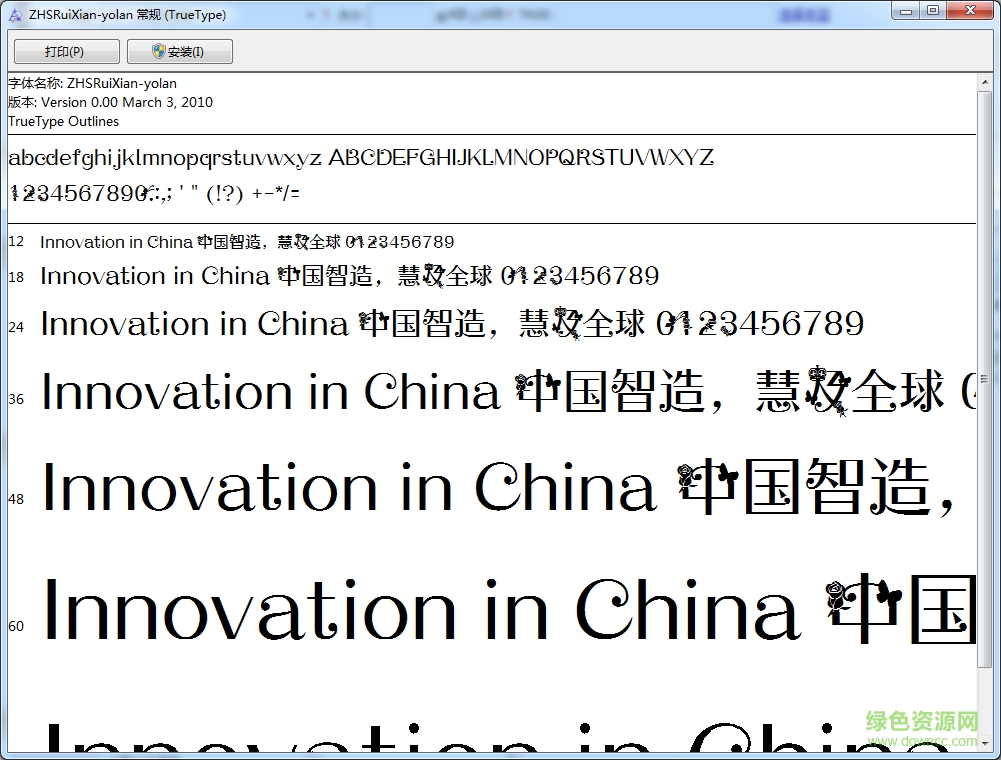
zhsruixian yolan是一款非常有個性的英文字體,字體極具美感,以花朵形狀裝飾文字,可直接安裝使用。快來綠色資源網(wǎng)下載體驗吧!
zhsruixian yolan字體是一款應用個設計行業(yè)的英文個性字體,該字體可以廣泛應用于廣告設計、宣傳海報、ppt、影視制作以及任何使用文字的領域。